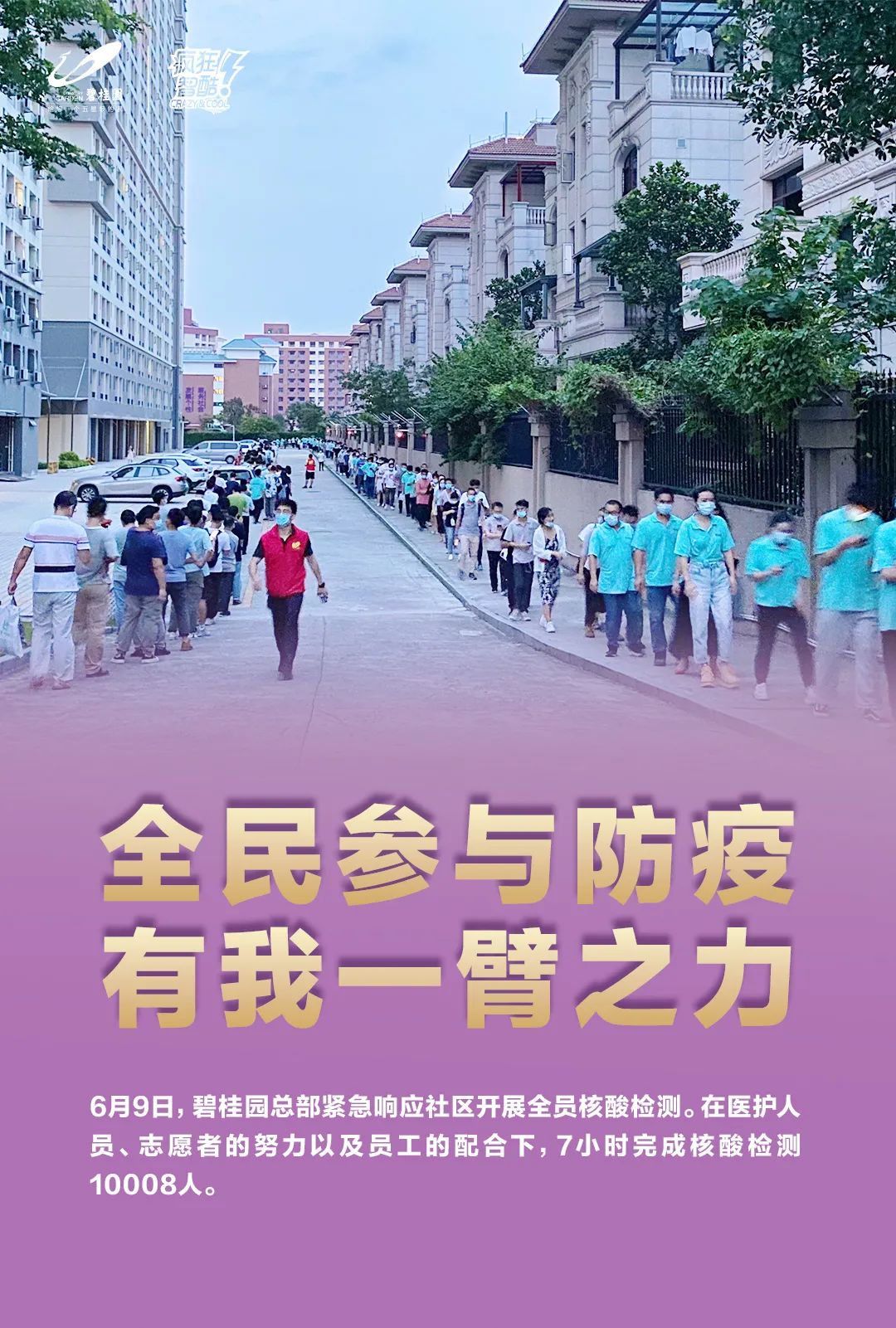
可口可乐在乎体
可口可乐在乎体 获4项设计大奖
全球知名品牌可口可乐公司在中国市场深耕了41年,在这里经营、生活、成长,也深受中华文化和精神启发。可口可乐企业价值观和中国文化中的“在乎”很有共鸣。“在乎”二字,细细品来,“在”,如破土幼芽,标示生命、初始、本能;“乎”,是将气息稳定、呼吸平稳。“在乎”,有“放在心上”之意。这份温和、不张扬的关怀和担当,是中国文化的独特表达,也是可口可乐中国的企业价值观。
为了致敬这份文化共鸣,可口可乐中国以重返中国早期的老商标字体为灵感原点,邀请汉字文化推广机构好字在和方正字库一起,创造了一套字体,命名为“可口可乐在乎体”。
作为一款全新的品牌定制字体,“在乎体”从情怀出发,用具象的设计方法,借由每一笔一划,表达中国人对“在乎”的理解和诠释——圆融、力量、担当、从容、进取,希望在数字化时代,为大家提供一种有人情味的字体选择。用在乎体,写在乎的事,给在乎的人。
写在乎的事,给在乎的人
“快乐水”出字体了!是“在乎”味儿的~
在中国市场深耕了41年,可口可乐公司这家全球化品牌,在这里经营、生活、成长,也深受这里的文化和精神启发。可口可乐中国的企业价值观和中国文化中的“在乎”很有共鸣。
“在乎”二字,细细品来,“在”,如破土幼芽,标示生命、初始、本能;“乎”,是将气息稳定、呼吸平稳。“在乎”,有“放在心上”之意。这份温和、不张扬的关怀和担当,是中国文化的独特表达,也是可口可乐中国的企业价值观。
为了致敬这份文化共鸣,可口可乐中国以重返中国早期的老商标字体为灵感原点,邀请汉字文化推广机构好字在和方正字库一起,创造了一套字体,命名为“可口可乐在乎体”。
作为一款全新的品牌定制字体,“在乎体”从情怀出发,用具象的设计方法,借由每一笔一画,表达中国人对“在乎”的理解和诠释——圆融、力量、担当、从容、进取,希望在数字化时代,为大家提供一种有人情味的字体选择。用在乎体,写在乎的事,给在乎的人。
结字上以欧体为主、笔法上以颜体为主,将严谨、合理的结构与饱满、粗壮的笔画融合在一起,给人以浑厚、庄重、规矩的第一印象;与此同时,运笔从容肯定,笔画起伏适宜,也体现着对书法传统的致敬。吸取传统精髓的同时,“在乎体”也结合现代审美:笔画紧实,简约、利落;折笔铿锵顿挫,整体状态劲健有力、精神十足。整套字体既有着传统意味,也不失现代感。
作为一家饮料公司,可口可乐中国对“水哲学”有着自己的理解,与中国文化对水的文化内涵的解读,有异曲同工之妙——从容又不失灵动;圆融与担当并重;上善若水,却不与万物争高下;既有 “水滴石穿”的坚韧,也有“海纳百川”的包容。“在乎体”的设计也尝试融入水的形态与精神。点画好似水滴,饱满、灵动,横画起笔收笔、弯钩转折处的弧度,也兼顾圆润和力量感,运笔自然、流畅,有如行云流水一般。
笔画都落在自然天成的圆中,呈现出圆融、包容的精神面貌。值得一提的是,不仅将水融于字,“在乎体”的笔画特征还彰显着书写意味,点画的形态,横画、竖画的笔法,都透着书写的韵律与活力。书写意味与水的形态相得益彰,赋予了“在乎体”厚而不重、流而不散、圆而不腻的精神面貌。
虽然是有着134年历史的老牌企业,但可口可乐在大众心目中一直是年轻、有活力的形象,是一个有着厚重历史的年轻灵魂。“在乎体”在设计上也呈现出这种活力向上的姿态:重心平稳、靠上,挺拔而有力量,笔势向右上倾斜,给人一种积极向上、青春飞扬的感觉,仿佛破土的幼芽,积极地向上生长。
尤其,作为一款汲取传统、创新成长的字体,在乎体在学习经典的时候,没有刻意追求纯熟状态,而是适度表现一种稚拙的萌态,快乐和生趣在一笔一画间流露——这种自然状态,也是这家公司希望传递的从容与活力。与此同时,在设计中,我们也一直思考如何将大家喜欢的“快乐水”畅爽感,融合进这款用“可口可乐”命名的字体。冰凉气泡冲击喉咙、在口中绽放,满足得打个嗝,结结实实透一口气,这份自在,被吸纳进“在乎体”的设计中:笔画开张有度,字面留有充足空间,字间保持合适的距离,让排列变得通透,阅读更加轻松、舒服,有如自在呼吸。
可口可乐在乎体全套字体包括7745个字符,其中汉字6769个,其他字符976个。“在乎体”西文的设计思路主要为配合中文的风格和气质而确定。字重较大,字形偏方并带有手写特征,笔形偏圆,带有倒角。在与中文风格匹配的同时,更体现年轻感和亲和力。中西文的搭配,也确保了“在乎体”在不同国家和地区的实用性。
“在乎体”是根据GB2312字符集设计制作的,但特别收录了GBK字符集中“凊”“鹍”等汉字,使用在乎体可以打出《千字文》的全文。我们还为可口可乐在乎体特别设计制作了中华传统民俗文化中的“合体字”以及陕西特有的“biang”字,利用在乎体的Opentype特性,可以方便地调用这些特别设计的字符。中国民间常用的喜庆汉字“囍”(属GBK字符集)也有收录。
可口可乐中国企业特别定制版字体中,还包含了主品牌标识:“在乎的笑脸”表情符号。来自于“在乎体”的中文笔画。
既有传统意味又符合现代审美,如水一般圆润、流畅又富有力量与活力,挺拔向上、自在从容,兼具这些特征的可口可乐在乎体,可以沉稳大气,也可以洒脱不羁,可以狂拽炫酷,也可以很接地气。